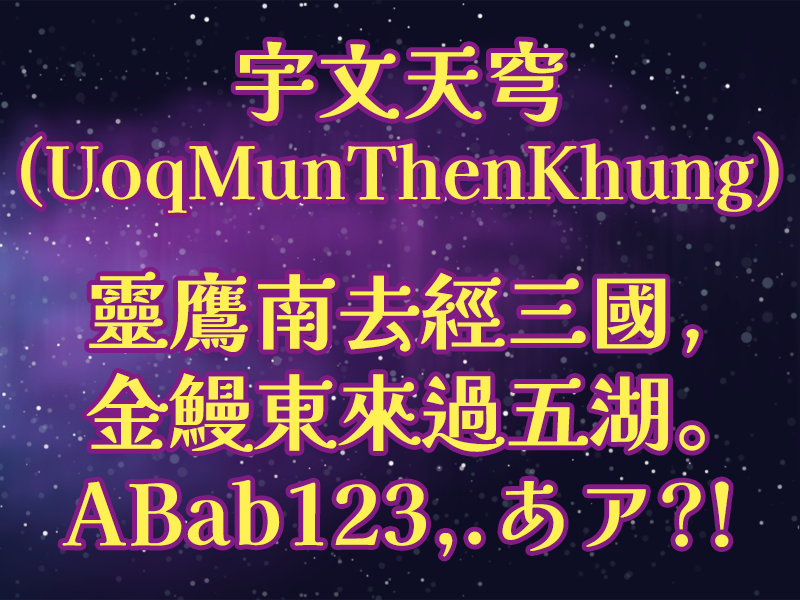
「宇文天穹(UoqMunThenKhung)」爲適用於繁體中文環境的開源字型,它以日本「解星計劃」開發的「解星」字型爲基礎,參照傳承字形標準化文件的推薦形體修改爲中文傳統字形,補製欠缺的漢字。
漢字字形向來千姿百面,印刷或屏顯的設計美觀需求與手寫書法的審美角度不盡相同,符合字理字源的傳統正字與書寫便捷的俗體變體也各有着眼點。而會使用傳統中文、繁體中文的地區,也有不同的敎育和非敎育標準或參考,這些標準或參考各有其立場,各有不同的適用與不適用場合,有時或會令有人顧此失彼之感。